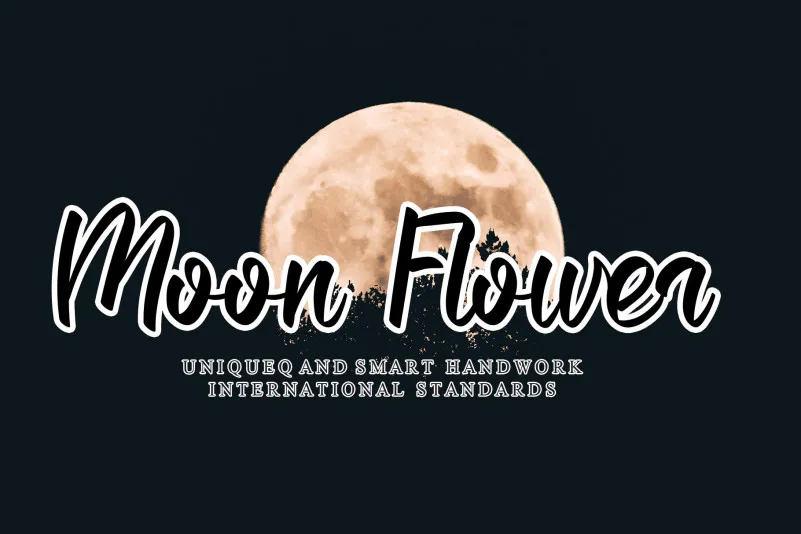
Moon Flower Script Font
A fonte Moon Flower Script é uma combinação suave e trendy de escrita a mão, que traz vida ao design digital. Seus caracteres distintos e bem redondos tornam esta fonte uma verdadeira obra-prima. Ela se destaca pela sua versatilidade incrível, permitindo que você crie designs impressionantes e únicos. Descubra o amor por seu estilo incomparável e explore suas possibilidades criativas. Ideal para quem procura um charme alegre e elegante em cada projeto. Sem dúvidas, é uma adição surpreendente à sua coleção de fontes. Com seu designer experiente e talentoso, andikastudio, essa Moon Flower Script oferece não apenas novos recursos estéticos, mas também um toque a mais de personalidade e originalidade aos seus projetos digitais. Tornando-se uma escolha inteligente para designers que buscam manter seu trabalho único e diferenciado em uma vasta gama de usos, desde anúncios até cartões de visita.